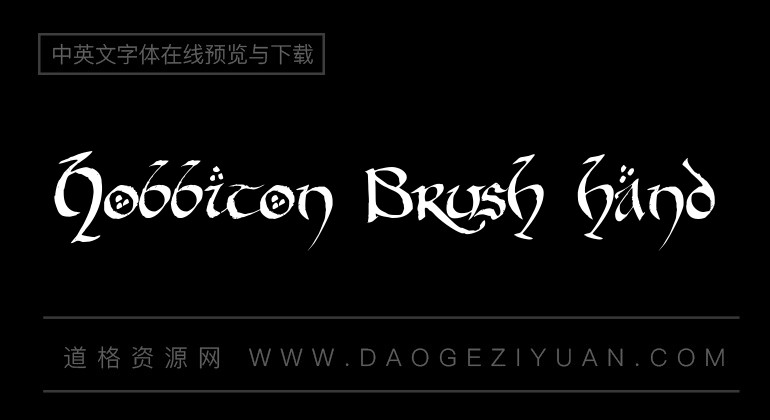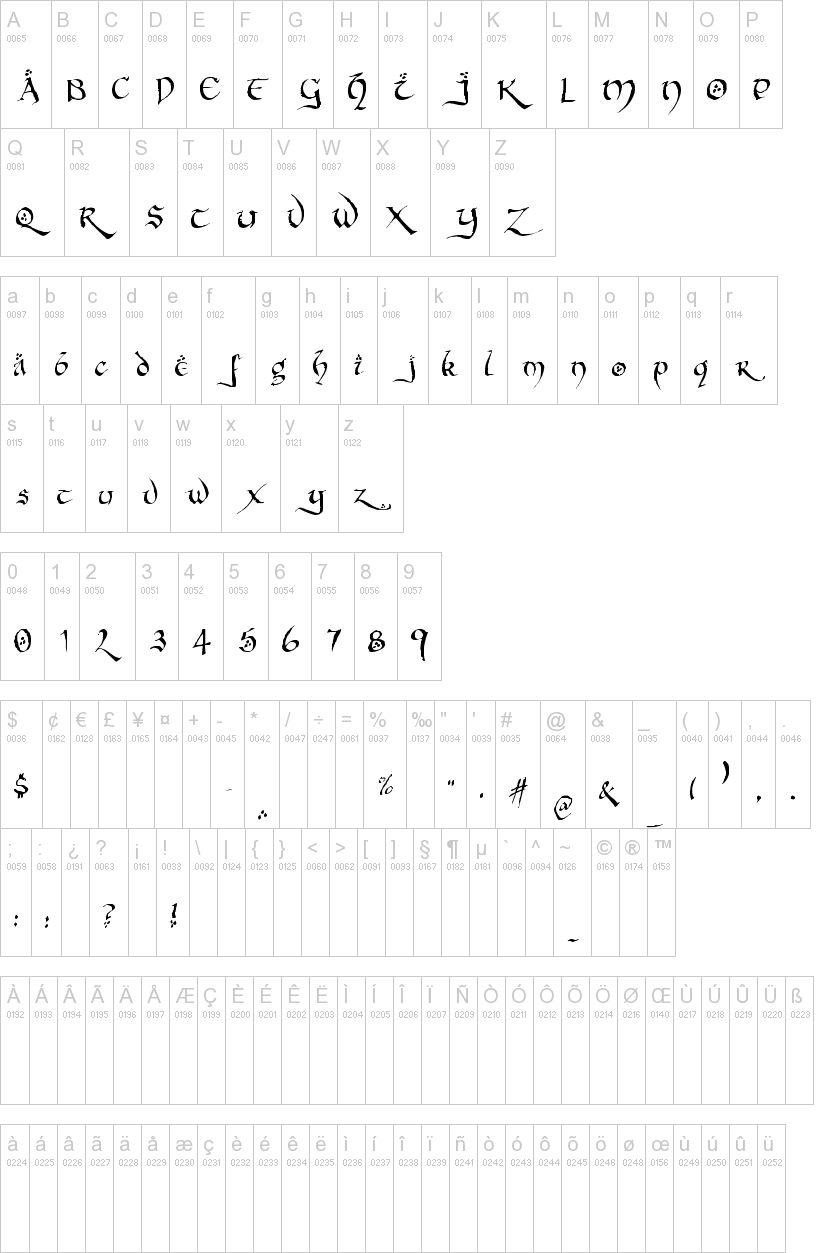
Hobbiton Brush hand
Hobbiton Brush Hand 是一款由Vernon Adams创作的手写体字体,它具有温暖、柔和、有趣的特点,以及一种抒情的气息。它的笔画流畅,自然,充满活力,使字体有更多的表现力。此外,Hobbiton Brush Hand 还拥有英文字母、数字和标点符号的完整集合,使它更加适合用于创作海报、卡片、T恤等。
Hobbiton Brush hand是一款非常不错的手写艺术字体,具有很好的视觉感,适合于文化类的宣传设计、商业类品牌的广告和产品包装设计以及个性化文字排版等较多场景。
Hobbiton Brush hand字符映射图